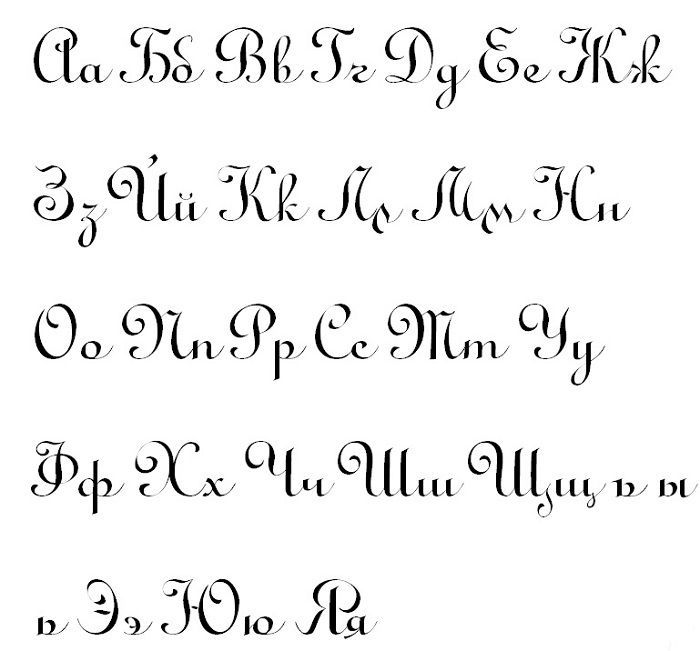
Красивые шрифты на русском для оформления: Красивые шрифты — русские скачать бесплатно
Элегантные рукописные шрифты
Цифровые рукописные шрифты — это идеальный способ придать документам вид написанных от руки. В этой коллекции SoftMaker предлагает большой выбор элегантных, красиво оформленных рукописных шрифтов.
Элегантные каллиграфические шрифты
«Элегантные каллиграфические шрифты» — коллекция из 150 каллиграфических шрифтов всех типов и стилей.
Многие шрифты коллекции поставляются с расширенными таблицами макетов OpenType для поддержки высококачественной международной типографии.